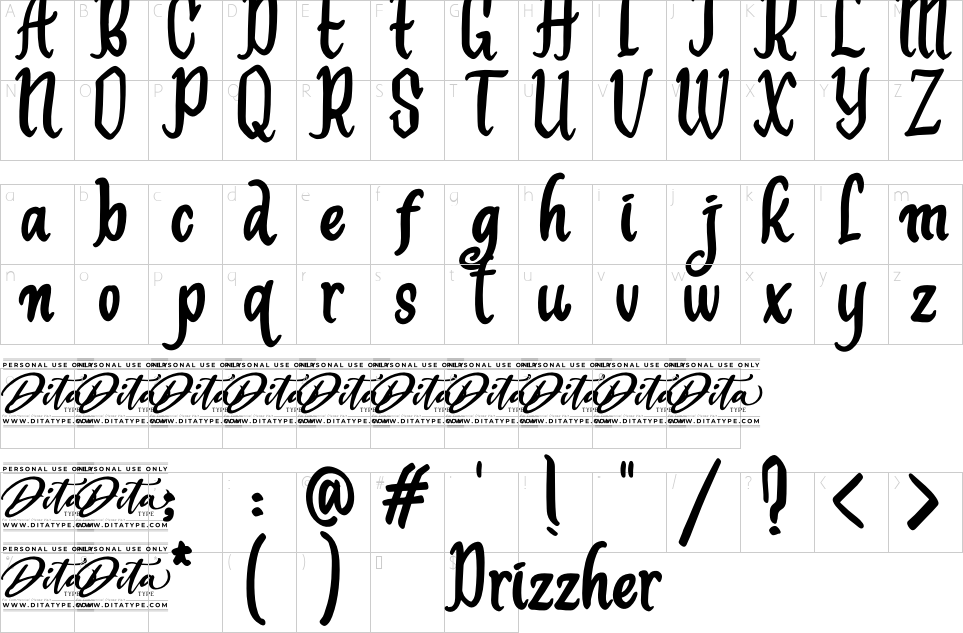
Descubra a delicadeza e a versatilidade do Drizzher Font para seus projetos digitais com esta elegante fonte grátis. Desenvolvida pela Dita Type, essa fonte curva e leve é perfeita para adicionar um toque de sofisticação aos teus design gráficos, textos ou interfaces. Com uma arquitetura minimalista que combina com diversos estilos, a Drizzher Font oferece uma experiência única em suas versões Windows e Mac. Descubra o encanto da Dita Type ao adquirir essa fonte de alta qualidade sem custos. Mais de 2.759 usuários já experimentaram a beleza desta fonte. Experimenta-a agora e inspire-te com um design gráfico que expressa sua individualidade, usando a Drizzher Font para seus projetos.